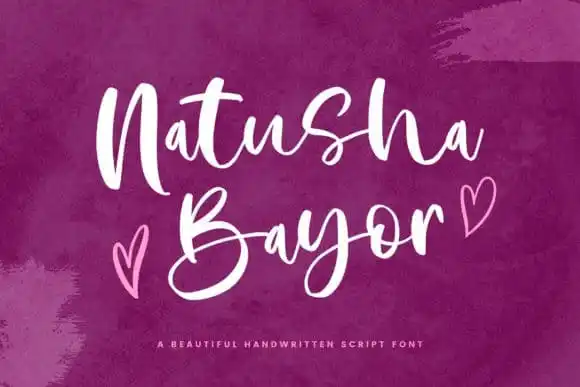
Natusha Bayor Script Font – Fonte Grátis
Natusha Bayor Script Font
Natusha Bayor Script é uma fonte tipográfica moderna criada para melhorar suas criações. Esse tipo de letra oferece um estilo simples mas atraente, que faz com que seja incrivelmente apropriado para projetos criativos e artísticos. Com seus traços suaves e belos, ela é perfeita para quem busca uma fonte que se destaca em qualquer projeto. A Natusha Bayor Script pode ser usada com propriedade em cartões de convite românticos para casamentos, arte de papelaria elegante, postagens no Facebook ou Instagram impressionantes e muito mais. Adoptando o seu incrivelmente versátil estilo, a Natusha Bayor Script irá transformar qualquer projeto. Perfeita tanto para um cenário formal quanto casual, ela é uma escolha perfeita para personalizar documentos, anúncios de eventos ou até mesmo mensagens pessoais. Aqui está uma oportunidade para você explorar diferentes aplicativos desta fonte enquanto se apaixona pelo seu design. Descubra por si mesmo o potencial deste tipo de letra moderna e elegante que vai transformar seus projetos!